Việc ứng dụng font chữ tattoo nghệ thuật thường gặp rắc rối khi các đường nét thanh mảnh bị đứt quãng hoặc lỗi hiển thị dấu tiếng Việt trên các bản in bao bì. Những sai sót kỹ thuật này làm giảm giá trị thẩm mỹ của sản phẩm, gây ảnh hưởng đến sự chuyên nghiệp của đơn vị kinh doanh. Xưởng In Viva cung cấp hệ thống kiểu chữ tattoo đẹp chuẩn sắc sảo, hỗ trợ đắc lực cho các công đoạn sản xuất và in ấn hiện đại.
Font chữ tattoo là gì và sức hút của phông chữ tattoo nghệ thuật?
Font chữ tattoo là một nhóm các phông chữ được lấy cảm hứng từ nghệ thuật xăm mình truyền thống và hiện đại, bao gồm nhiều phong cách khác nhau như Gothic cứng cáp, Script uốn lượn hay font chữ La Mã tattoo cổ điển. Đặc trưng của dòng phông này là sự cầu kỳ trong từng đường nét, mang đậm cá tính mạnh mẽ, phóng khoáng và có tính biểu đạt nghệ thuật rất cao.
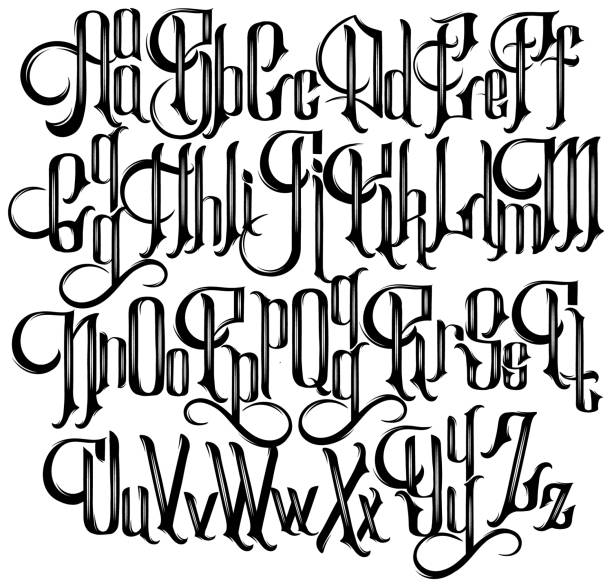
05 Ứng dụng phổ biến của font chữ tattoo đẹp trong thực tế
Vẻ đẹp cá tính và tính biểu đạt mạnh mẽ của mẫu chữ xăm nghệ thuật nâng tầm giá trị cho nhiều ấn phẩm truyền thông của đơn vị:
- Thiết kế bao bì mỹ phẩm và thời trang bụi bặm: Sử dụng font chữ tattoo cho các dòng hộp giấy Ivory hay túi giấy Kraft đựng quần áo streetstyle. Những nét chữ nghệ thuật tạo cảm giác sản phẩm có gu riêng, dễ dàng tạo thiện cảm với phân khúc khách hàng yêu thích sự phá cách.
- Sản xuất bộ nhận diện sự kiện âm nhạc và văn hóa: kiểu chữ tattoo đẹp là lựa chọn phù hợp cho các tiêu đề lớn trên bạt backdrop hoặc banner đón khách. Sự kết hợp giữa nét chữ phóng khoáng và kỹ thuật in rực rỡ giúp không gian sự kiện toát lên sự năng động và chuyên nghiệp.
- Gia công in UV trên các vật phẩm cá nhân: Logo và slogan dùng font chữ đẹp tattoo được in trên bình giữ nhiệt kim loại hoặc sổ tay bìa da. Độ sắc sảo của tệp vector giúp các nét uốn lượn hiển thị rõ ràng trên các bề mặt sẫm màu, tạo vẻ ngoài bền bỉ theo thời gian.
- Trang trí voucher và thẻ thành viên đặc quyền: Một dòng chữ vinh danh dùng form chữ tattoo trên thẻ tri ân giúp tạo điểm nhấn độc đáo, mang lại cảm giác được trân trọng cho người sở hữu các tấm thẻ này.
- In nung gốm sứ bộ lưu niệm: Hình ảnh chữ nghệ thuật dùng phông chữ tattoo in nung trên men sứ trắng mang lại vẻ đẹp nhã nhặn nhưng đầy phá cách cho các bộ ấm chén, là hiện vật trưng bày tinh tế cho các buổi lễ ký kết.
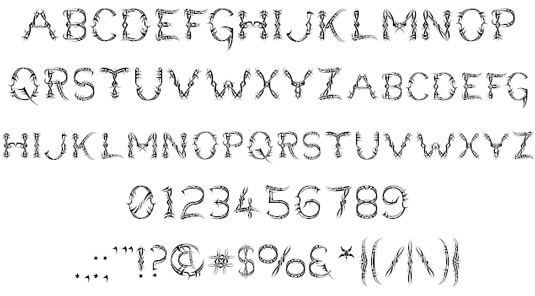
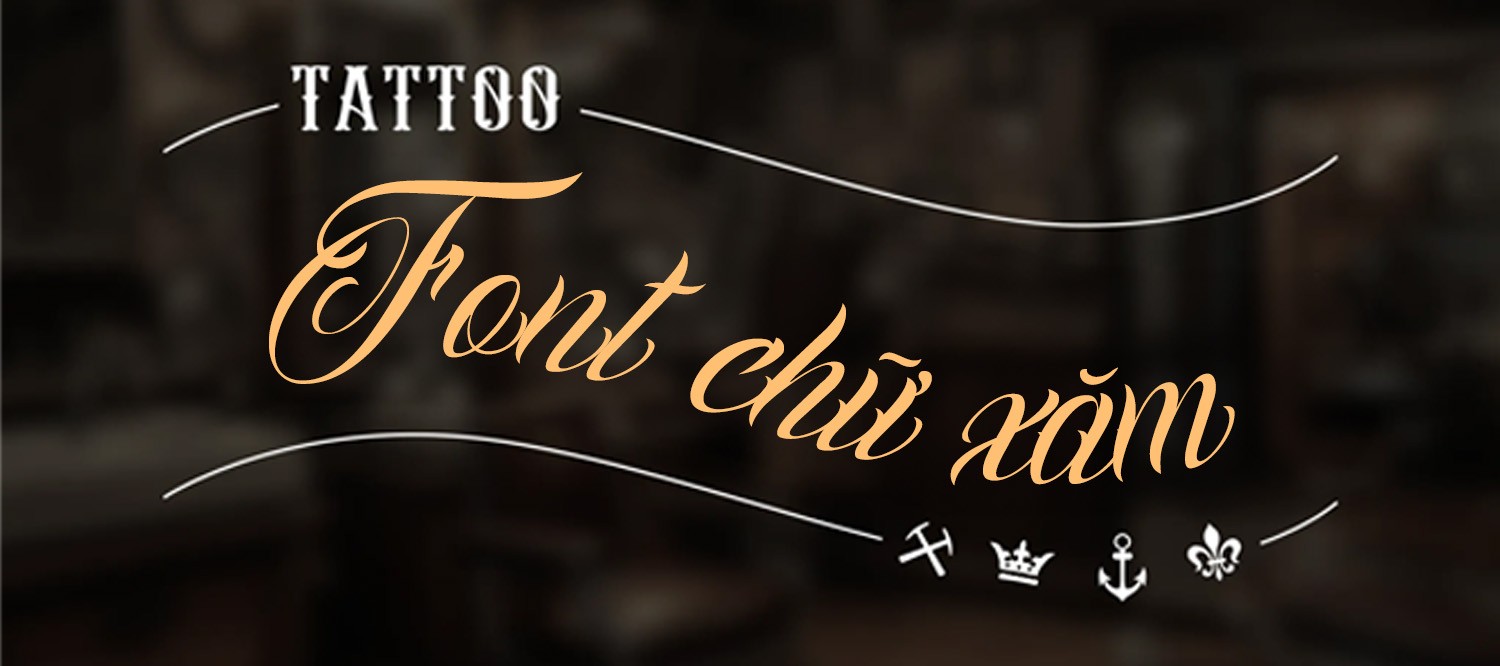
04 Lưu ý kỹ thuật khi sử dụng kiểu chữ tattoo đẹp Việt hóa
Để hệ thống ký tự uốn lượn hiển thị sống động và bền màu trên các thành phẩm thực tế như bao bì giấy hay hiện vật tri ân đối tác, designer cần chú trọng:
- Kiểm soát độ dày nét theo vật liệu: font chữ xăm tattoo thường có các nét nối và hoa văn rất mảnh. Khi in trên túi giấy Kraft có độ hút mực cao, bạn nên chọn biến thể có nét dày để tránh tình trạng mực loang làm chữ bị dính vào nhau gây mất dáng chữ hoặc mờ nhòe.
- Tối ưu đường Path cho gia công bế nổi: Bước này quan trọng khi sản xuất nắp hộp cứng dập nổi logo doanh nghiệp. Kỹ thuật viên cần làm mượt từng điểm neo tròn trong file vector giúp khuôn bế thực hiện chính xác, tạo hiệu ứng nổi khối rạng rỡ cho các chi tiết uốn lượn mà không làm rách giấy.
- Thiết lập hệ màu CMYK cho dải màu rực rỡ: Chữ xăm thường đi cùng các tông màu vàng đồng hoặc cam đất. Designer cần hiệu chỉnh hệ màu CMYK chuẩn in ấn tại xưởng và yêu cầu mẫu thử để đảm bảo màu chữ sau in không bị ám xám hay mất sắc độ so với bản vẽ font chữ tattoo online.
- Đảm bảo tính chính xác của dấu tiếng Việt: Do dòng phông này có cấu trúc nét phức tạp, bạn nên kiểm tra kỹ khoảng cách các lớp màu để đảm bảo dấu thanh không bị chồng lấn quá dày gây hiện tượng gồ ghề bề mặt sau khi gia công cán màng bảo vệ thành phẩm.